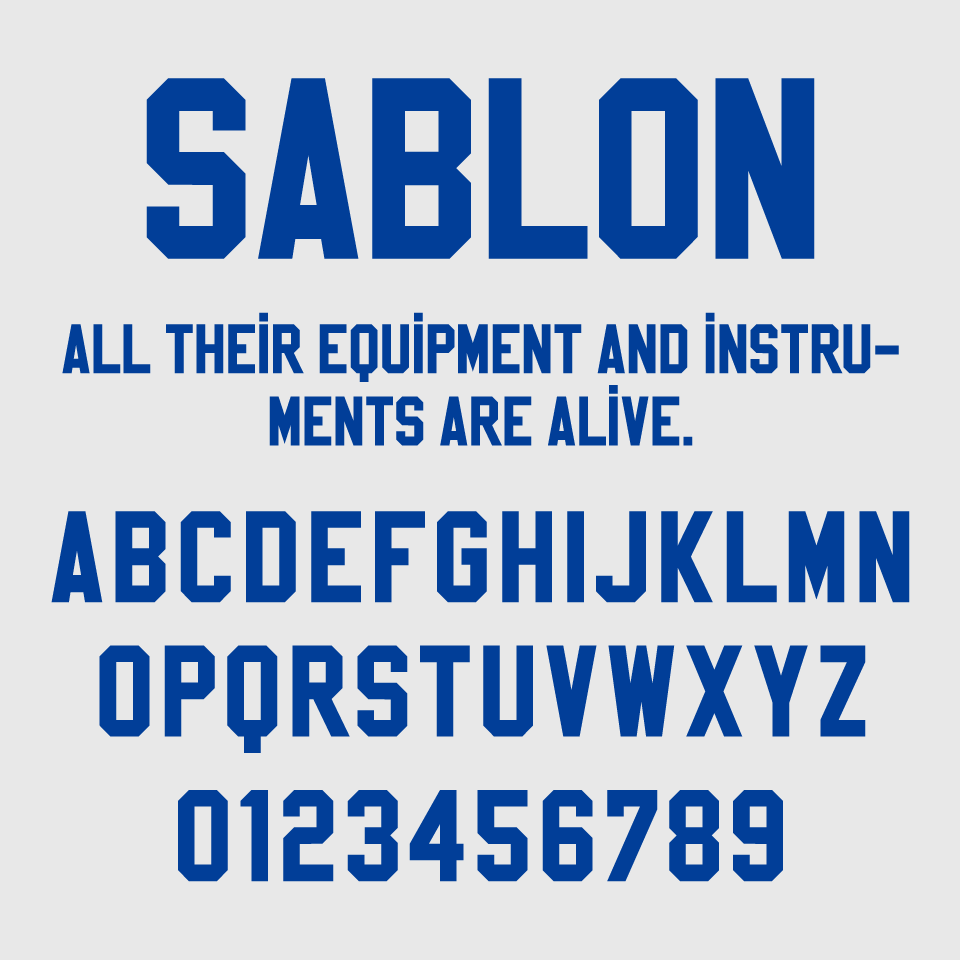
Sablon フォントは、無骨で直線的なエッジが特徴の、インダストリアルな雰囲気をもつサンセリフフォントです。
軍用車両や工具箱にスタンシルされた文字を思わせる力強い印象で、非常に視認性が高く、遠くからでもしっかり読める設計になっています。ドットがきいたSのように、細部に個性を持たせている点も魅力です。
野球やバスケのユニフォームを彷彿させるようなのようなデザインです。